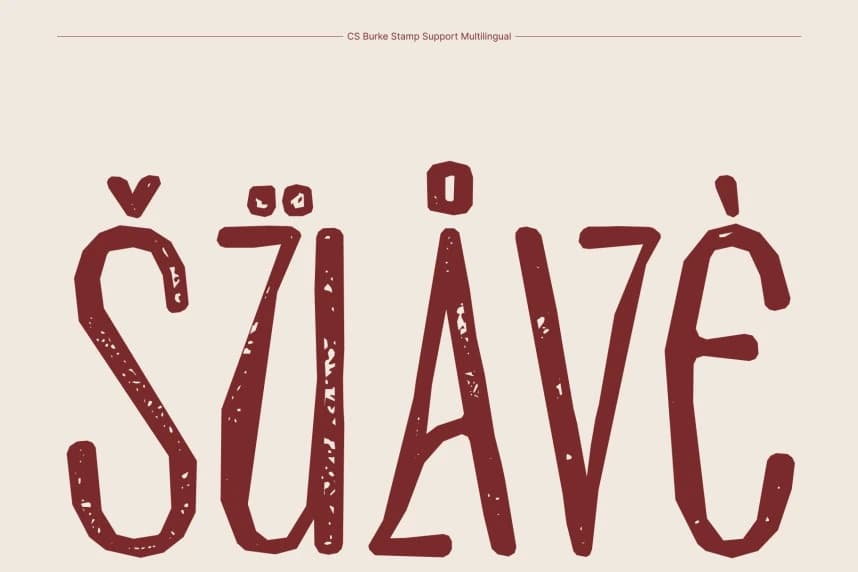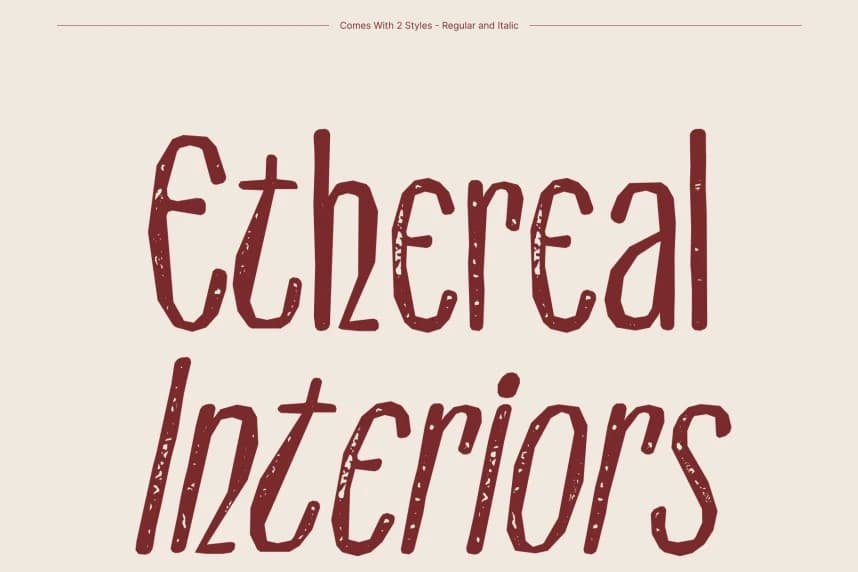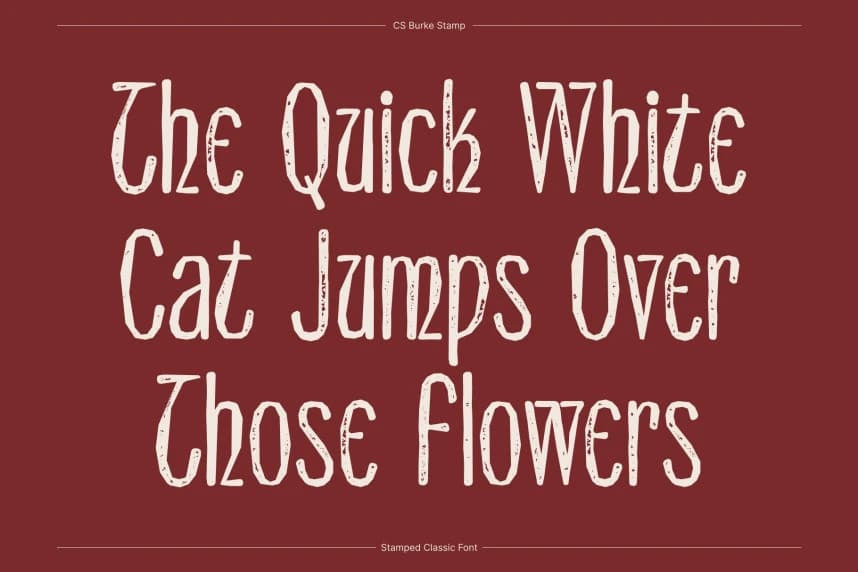
CS Burke Stamp Yazı Tipi
CS Burke Stamp Font – Klasik Sans-Serif ile Modern Zarafet, Modern Sans-Serif ile Zamansız Lüks. Bu, zarif bir sans-serif gösterim yazı tipidir ve şık modern minimalizm ile klasik sofistikasyonu birleştirir.
CS Burke Stamp Font – Klasik Sans-Serif, Modern Zarafet ile. Modern Sans-Serif, Zamansız Lüks ile. Bu, şık modern minimalist yaklaşımıyla klasik sofistikasyonu birleştiren rafine bir sans-serif gösterim yazı tipidir.